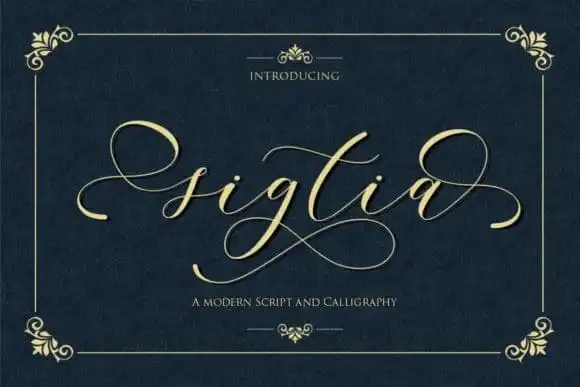
Sigtia Calligraphy Font – Download Grátis
A Sigtia Calligraphy Font é uma tipografia script com um charme natural que vem diretamente do traço de um lápis. Essa fonte apresenta ligaturas e alternativas encantadoras perfeitamente adaptadas para qualquer projeto criativo. Ela foi criada pelo designer Gilar Studio e tem um estilo elegante e aconchegante, característico de escritas feitas a mão. O seu design original garante uma personalidade única, adorável e cheia de vida, tornando-a perfeita para diversas aplicações, desde convites e estacionários até publicações no Instagram, anúncios, embalagens de produtos, selos, fotos, marca d’água, eventos especiais, logomarcas, assinaturas, citações, cartões de visita ou simplesmente em qualquer projeto gráfico.